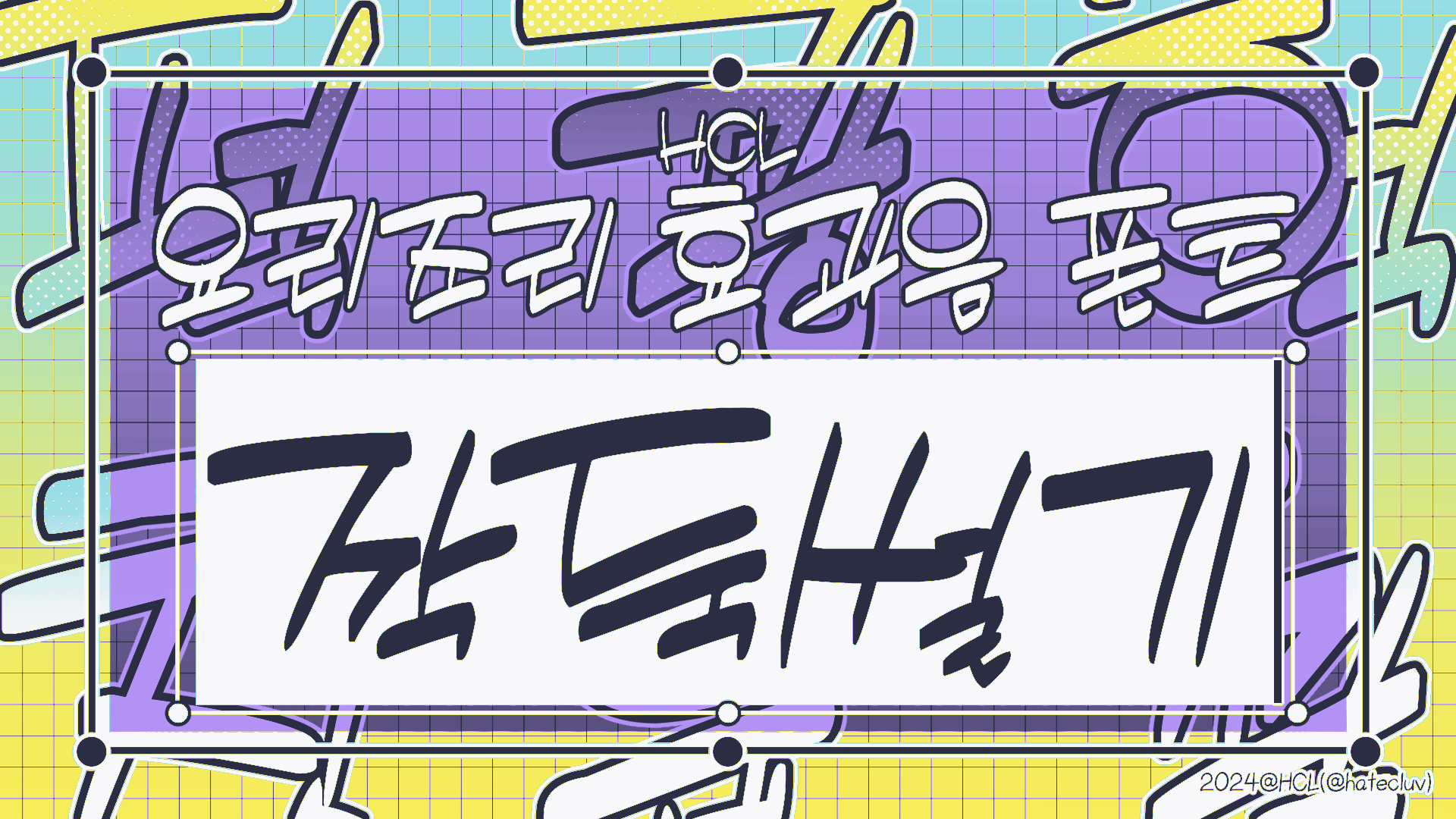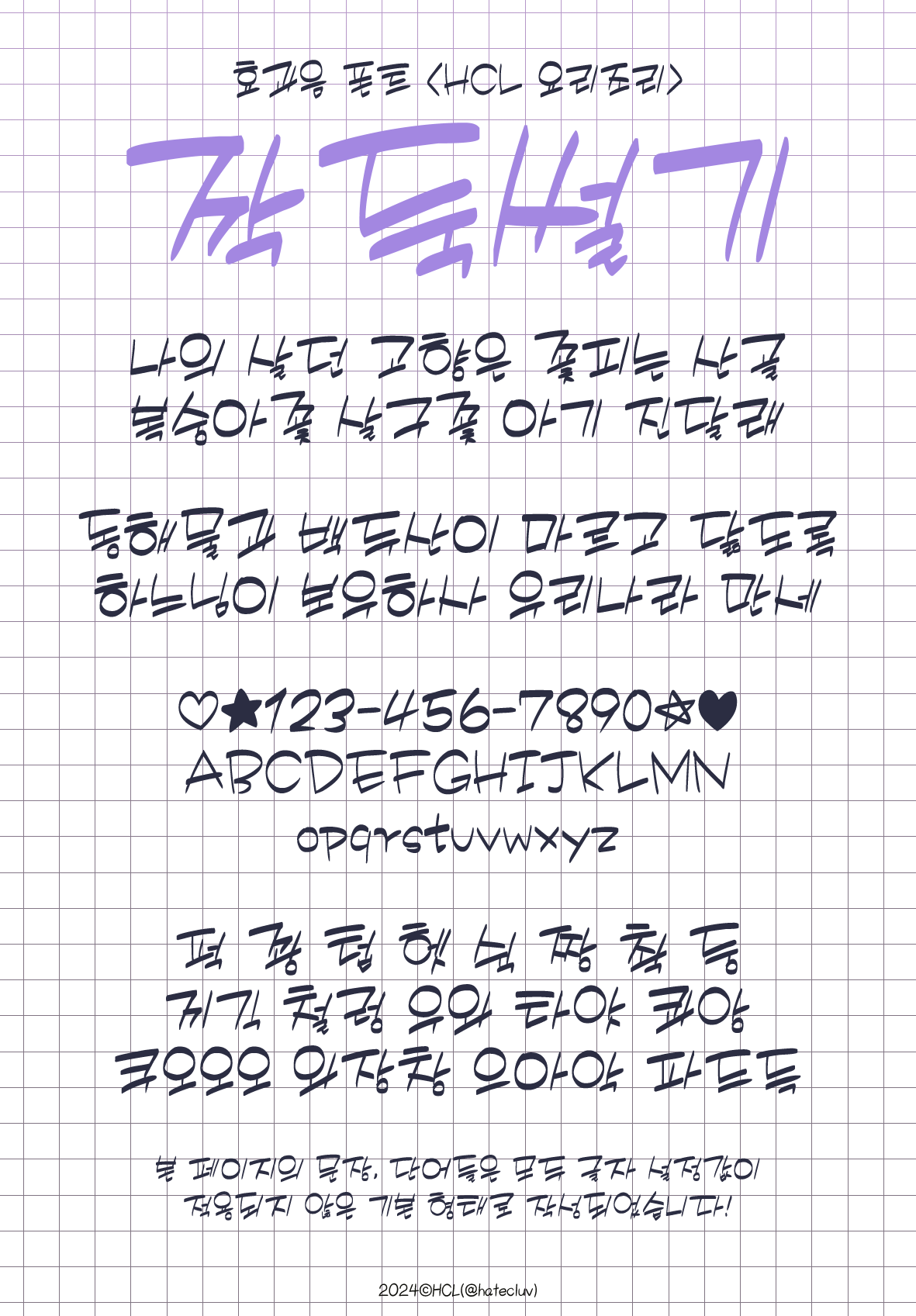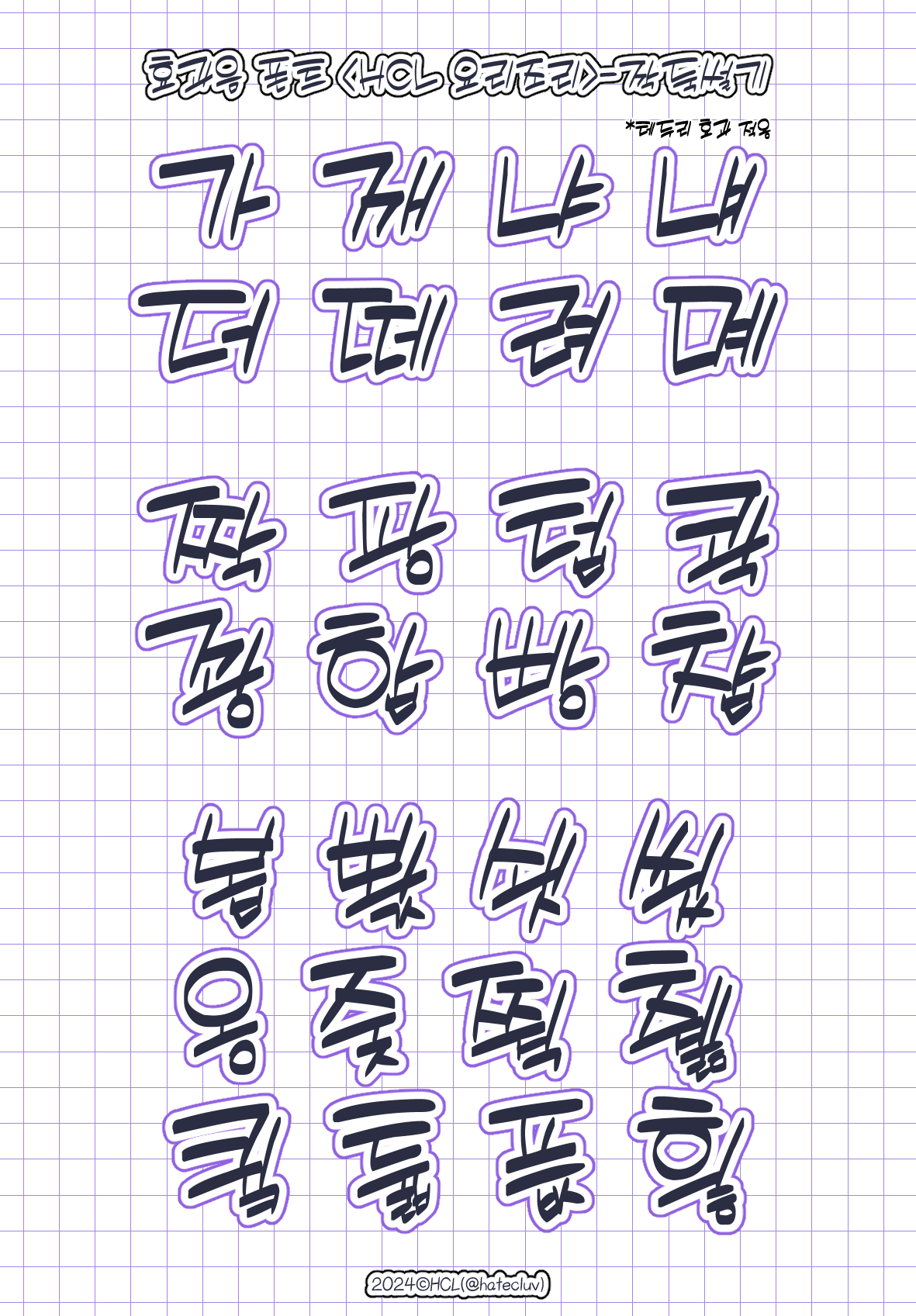
만화 효과음 느낌의 캘리그라피 폰트 5종 시리즈 <HCL 요리조리> 중 <깍둑썰기> 입니다. 카레에 들어가는 재료들처럼 각진 모양을 표현한 글꼴입니다.
캐주얼 스타일의 웹툰 작화와 일상적 / 가벼운 / 명랑한 분위기의 컷에 범용적으로 사용하기 좋습니다.
HCL 요리조리 깍둑썰기